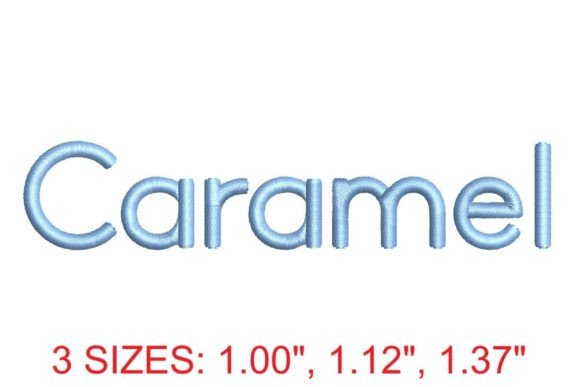
Caramel Embroidery Font
適切なデザイン要素を見つけるのは難しい場合がありますが、Caramel Embroidery Fontは作品を即座に引き立てる優れたコレクションを提供します。
POD(オンデマンド印刷)製品、結婚式の招待状、またはソーシャルメディアのグラフィックを作成している場合でも、Caramel Embroidery Fontは理想的です。